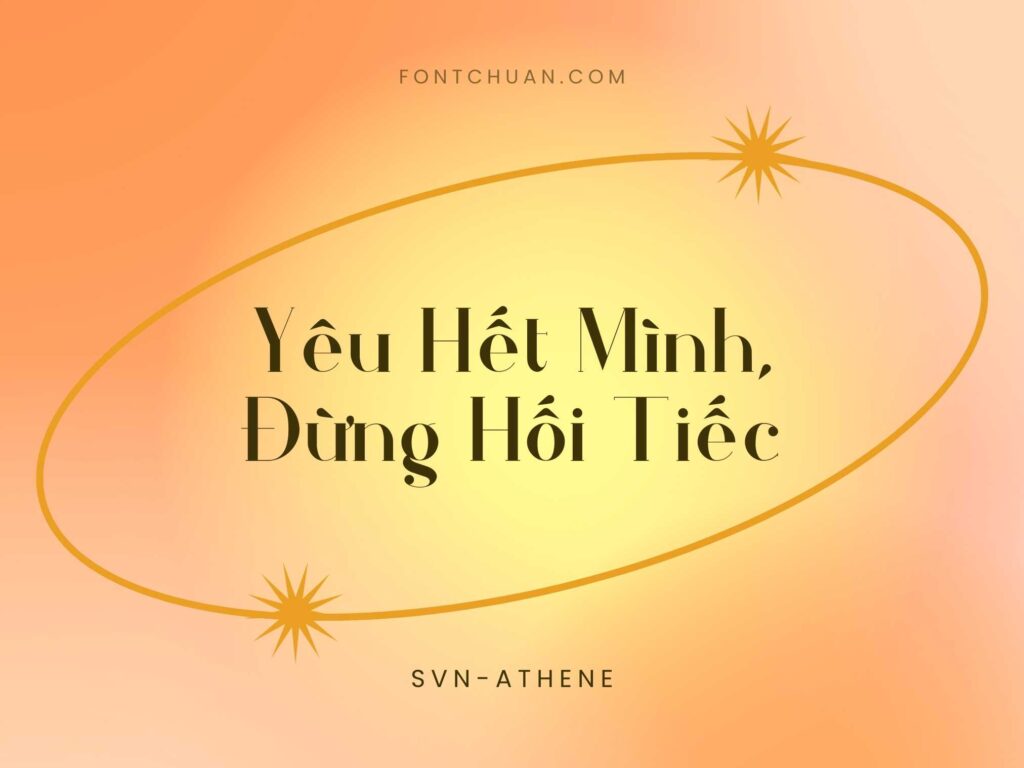
Font SVN Athene Việt Hóa
Athene là một kiểu chữ serif thanh lịch với nét hiện đại và hình học, được thiết kế bởi Matt Ellis. Font này nổi bật với sự kết hợp giữa các đường nét tinh tế và cấu trúc hình học, tạo nên sự cân đối và thu hút trong thiết kế. Athene bao gồm cả chữ hoa và chữ thường, cùng với các ký tự số và ký hiệu, phù hợp cho nhiều ứng dụng khác nhau nhưng đặc biệt thích hợp làm font chữ hiển thị. Font đã được Việt hóa để hỗ trợ tiếng Việt bởi Styleno.1 Fonts, đồng thời hỗ trợ nhiều ngôn ngữ khác, giúp mở rộng phạm vi sử dụng trên toàn cầu. Font này được thành viên của Font Chuẩn sưu tầm và chia sẻ, đáp ứng nhu cầu của bạn đọc và ứng dụng thực tế vào các dự án thiết kế.
Đặc điểm thiết kế của Athene bao gồm các đường nét thanh mảnh, độ tương phản cao và sự kết hợp giữa phong cách serif cổ điển với yếu tố hình học hiện đại, tạo nên sự độc đáo và tinh tế. Font này phù hợp cho các ứng dụng như thiết kế bìa sách, tiêu đề, áp phích, logo và các dự án sáng tạo khác. Các ngành nghề phù hợp bao gồm quảng cáo, nghệ thuật, thiết kế đồ họa và xuất bản.